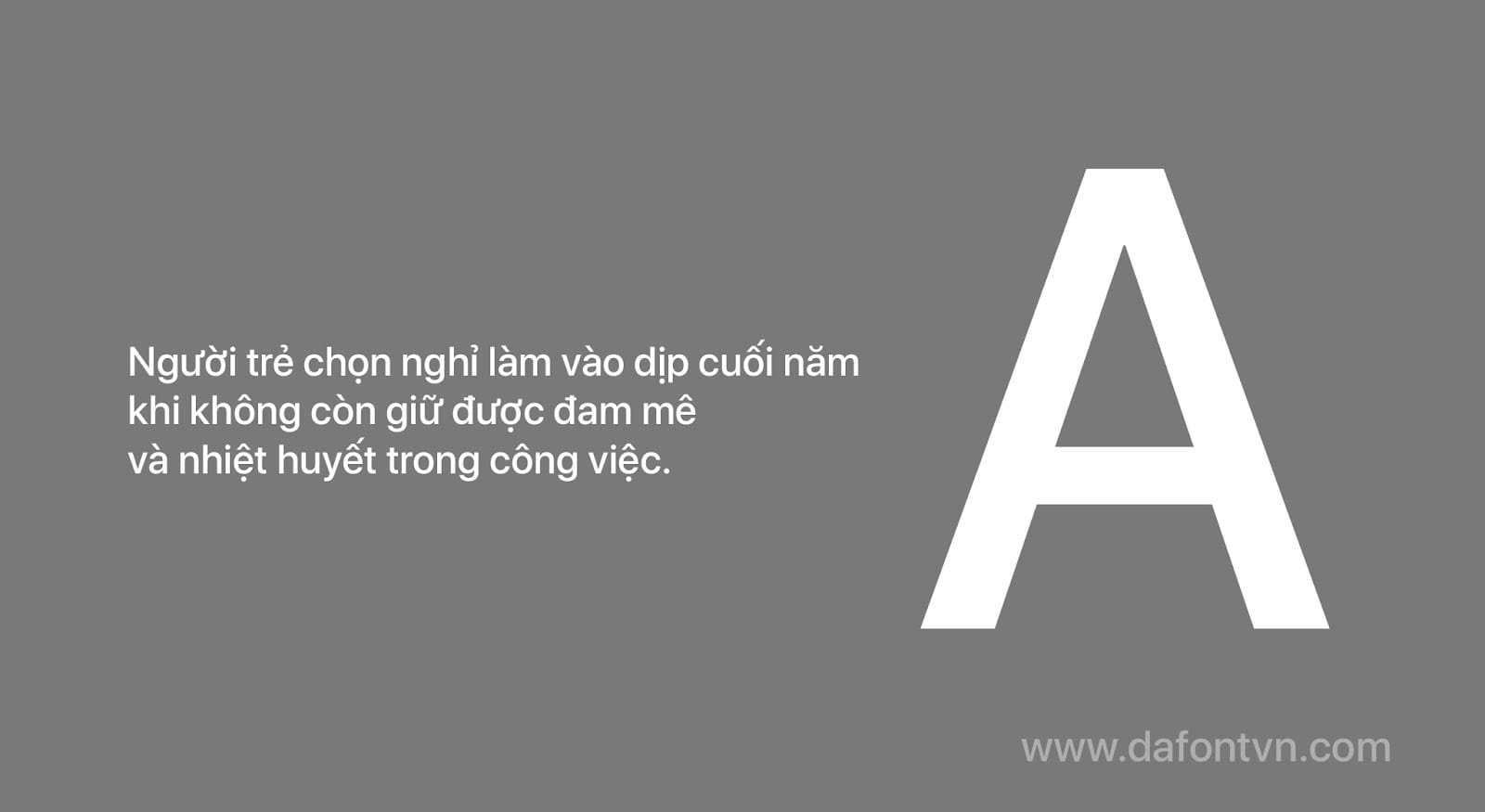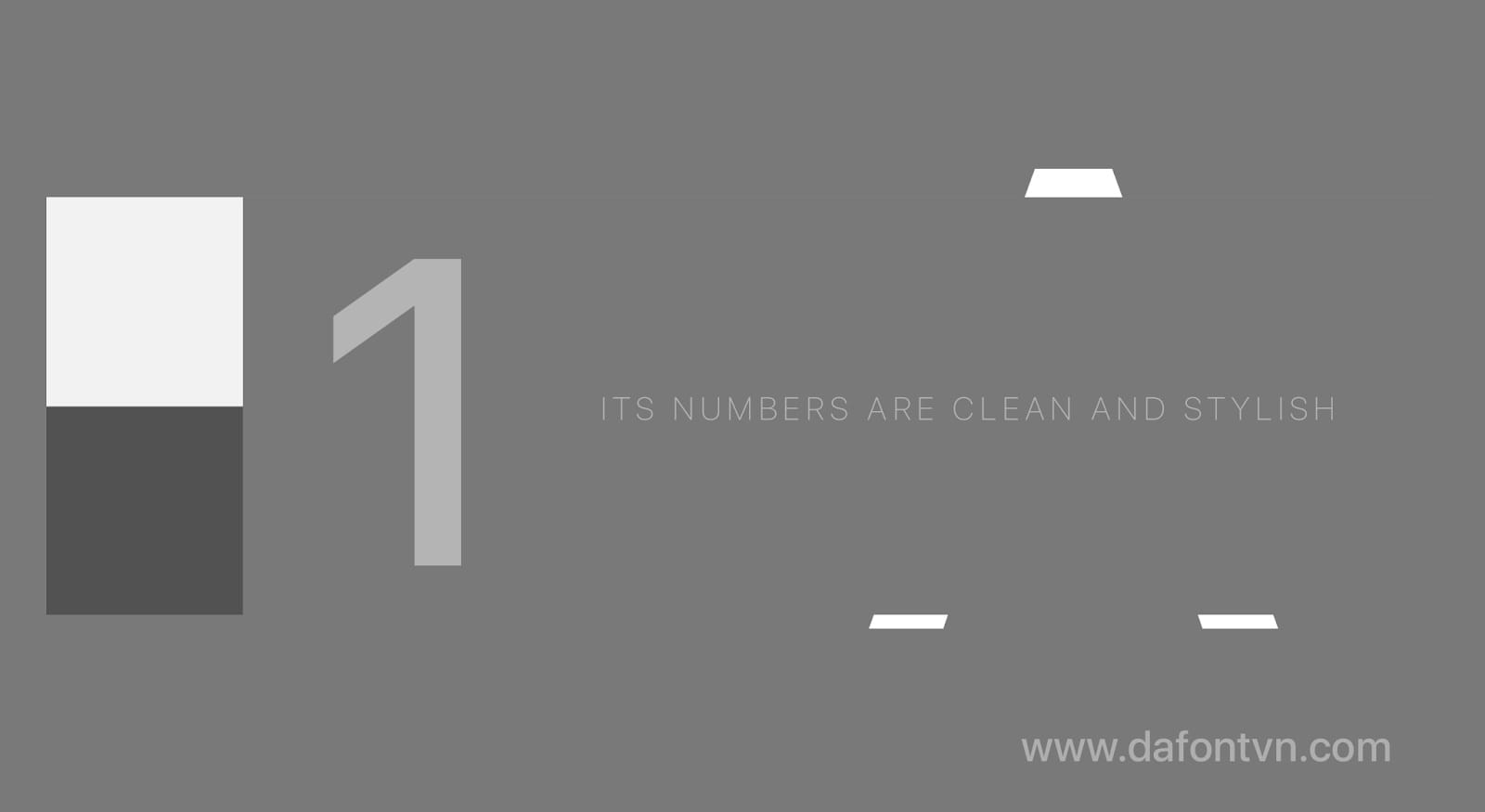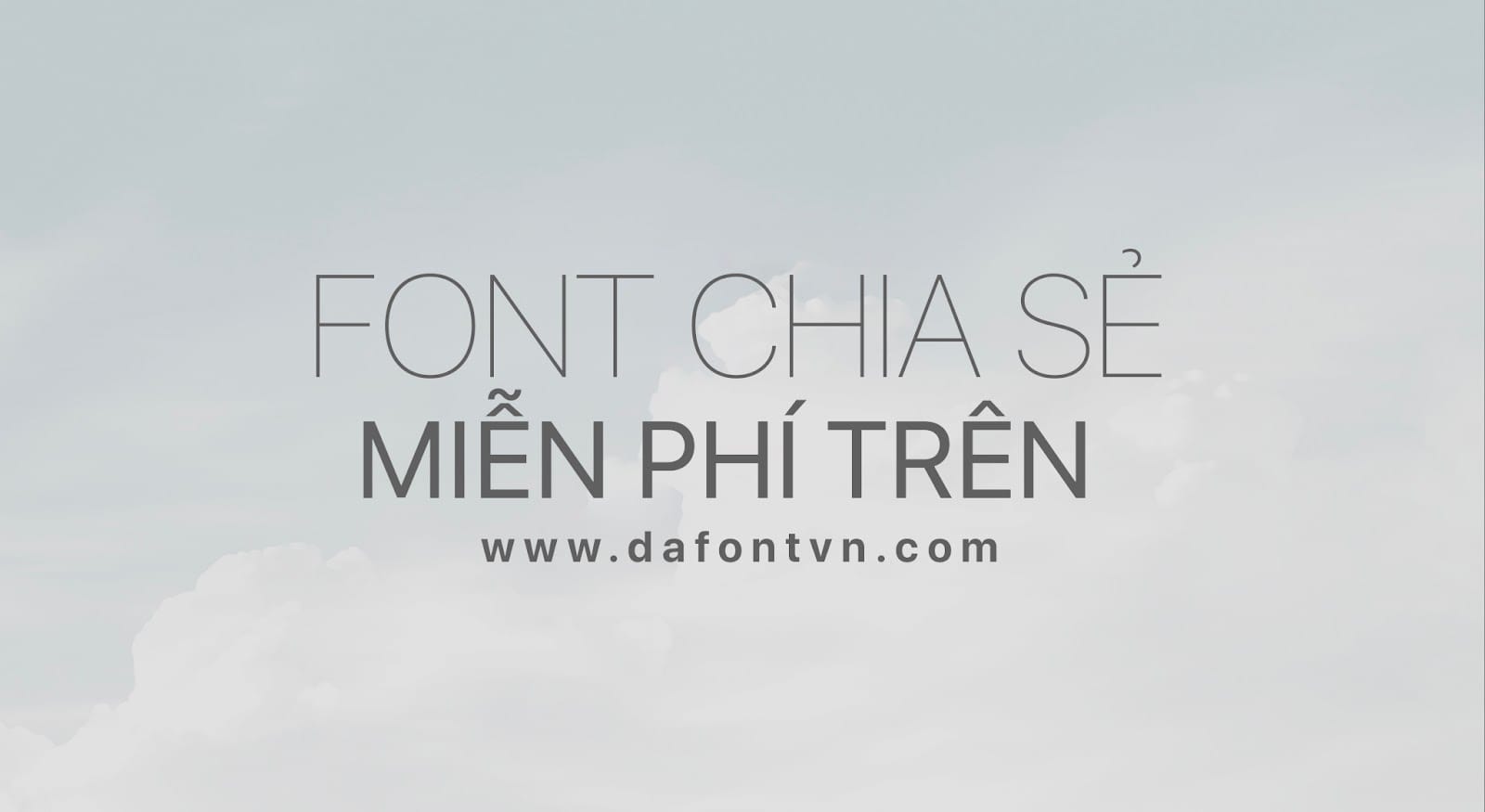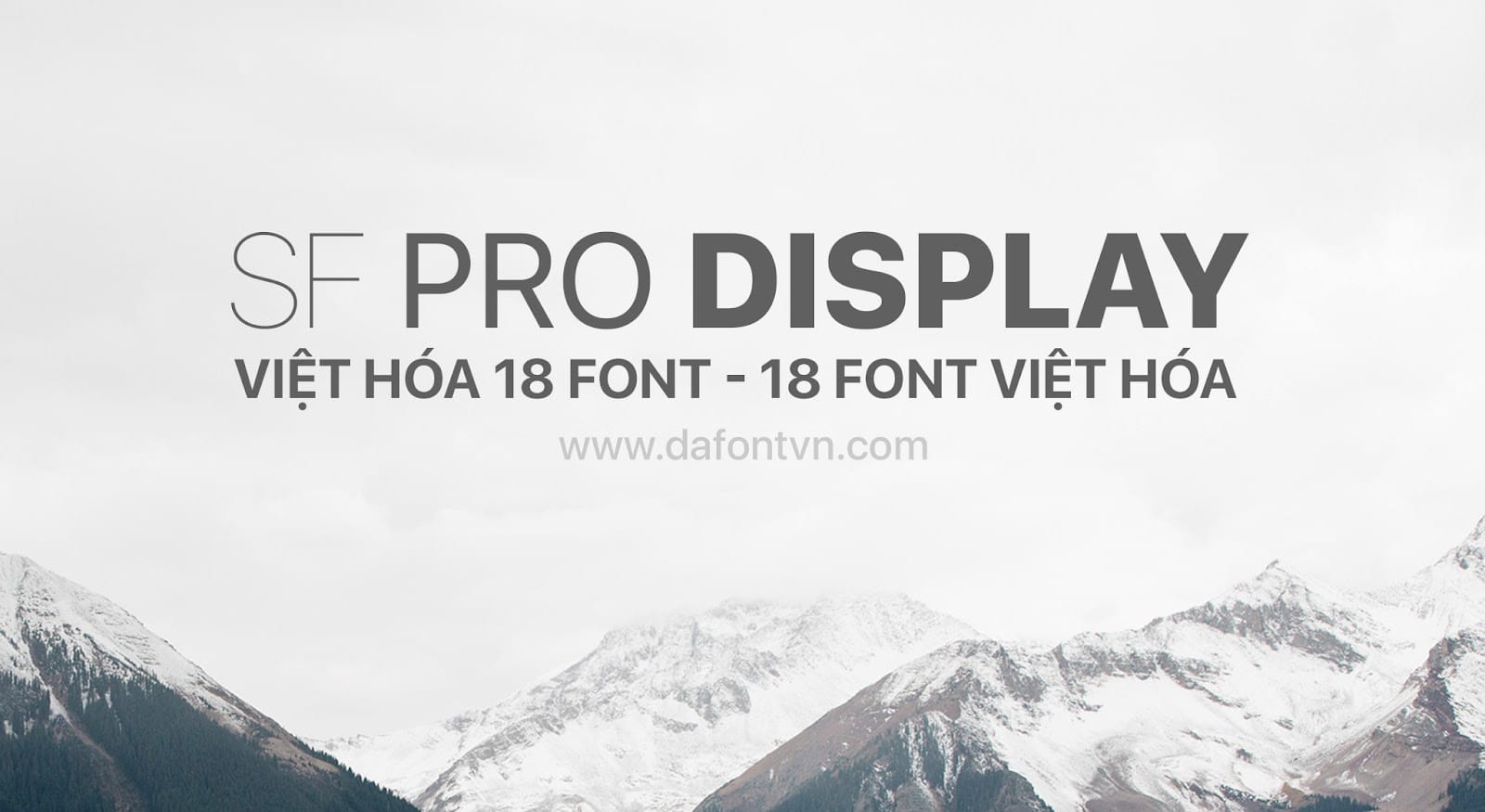
SF Pro Display là kiểu font sans-serif linh hoạt, là font chữ được sử dụng trong hệ thống cho iOS, iPad OS, macOS và tvOS. SF Pro có 9 weight, kích thước quang học thay đổi để dễ đọc tối ưu và bao gồm một biến thể làm tròn. SF Pro hỗ trợ hơn 150 ngôn ngữ bằng hệ thống chữ viết Latinh, Hy Lạp và Cyrillic. Trong đó hỗ trợ đầy đủ ngôn ngữ Tiếng Việt.
Bộ font SF Pro Display Việt Hóa bao gồm đầy đủ 18 font được chỉnh sửa và hoàn chỉnh cũng như kerning lại.